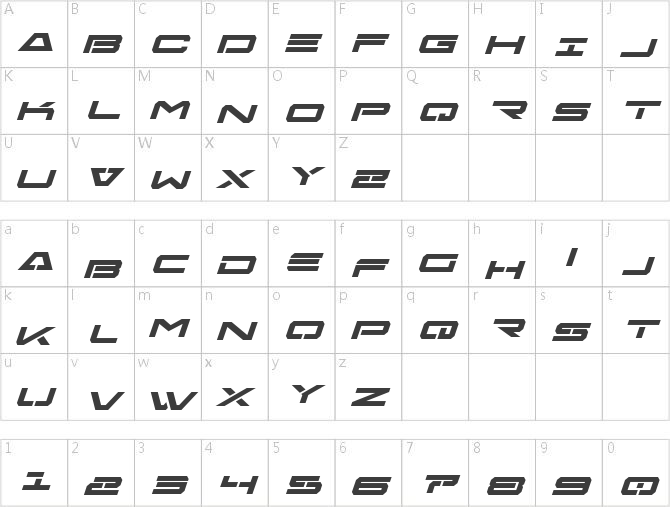
freeagentboldexpandital
freeagentboldexpandital介绍
freeagentboldexpandital字体字库是一款让人赏心悦目、百看不厌的英文字体,适合各类广告和产品包装设计应用,字体大小0.02MB,格式为ttf字体,上传用户是M_墨董,作者/版权方为未知